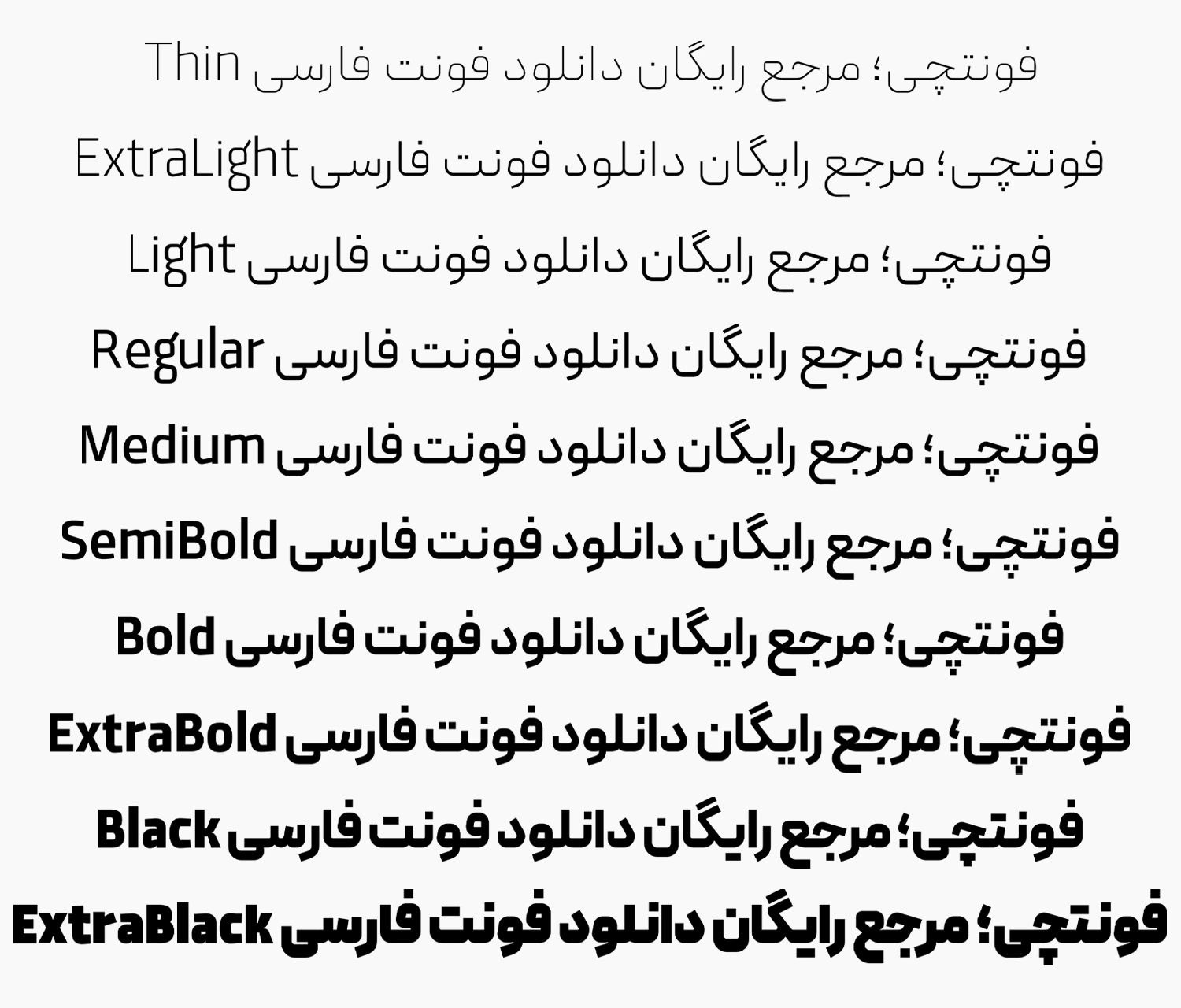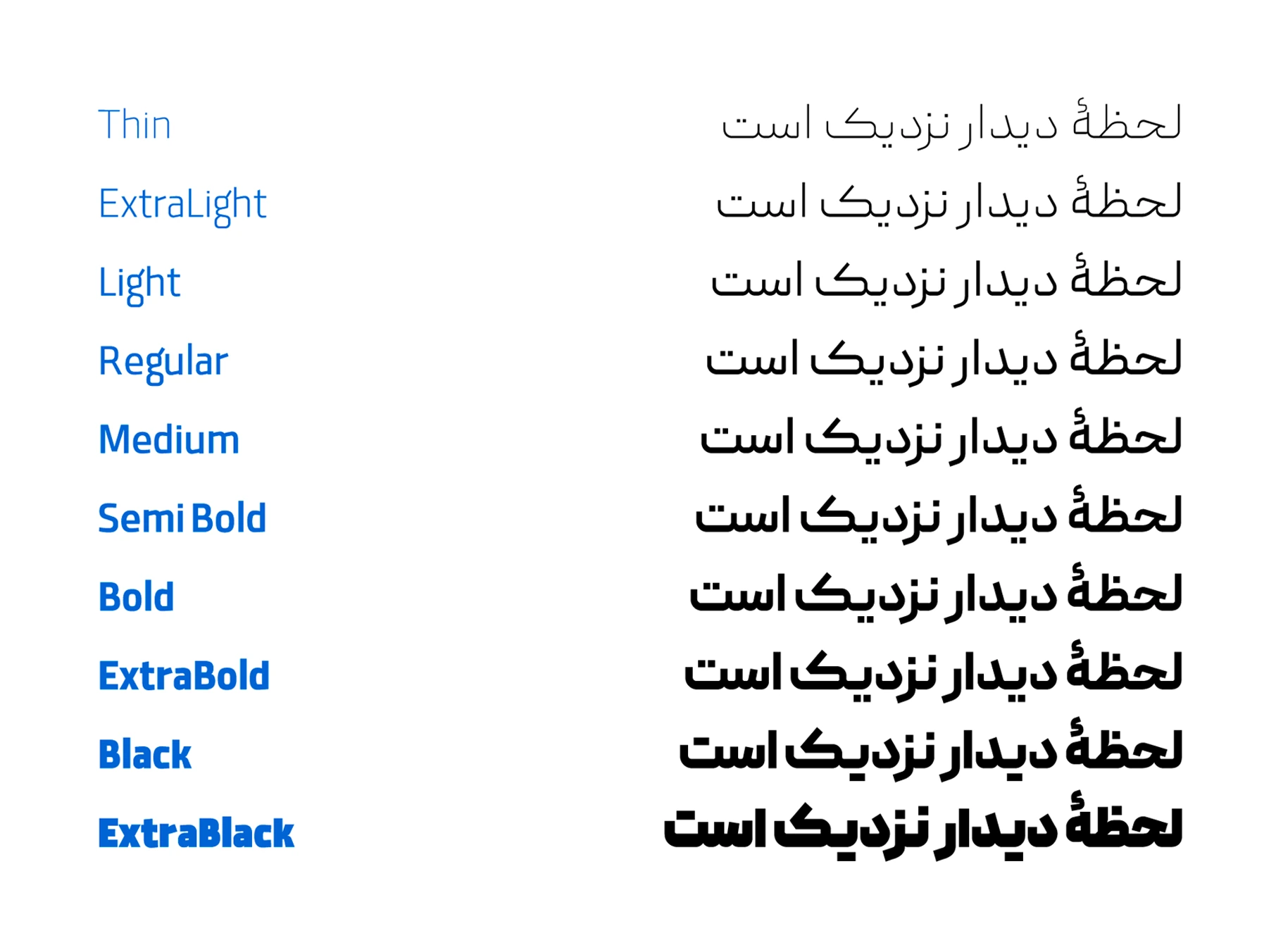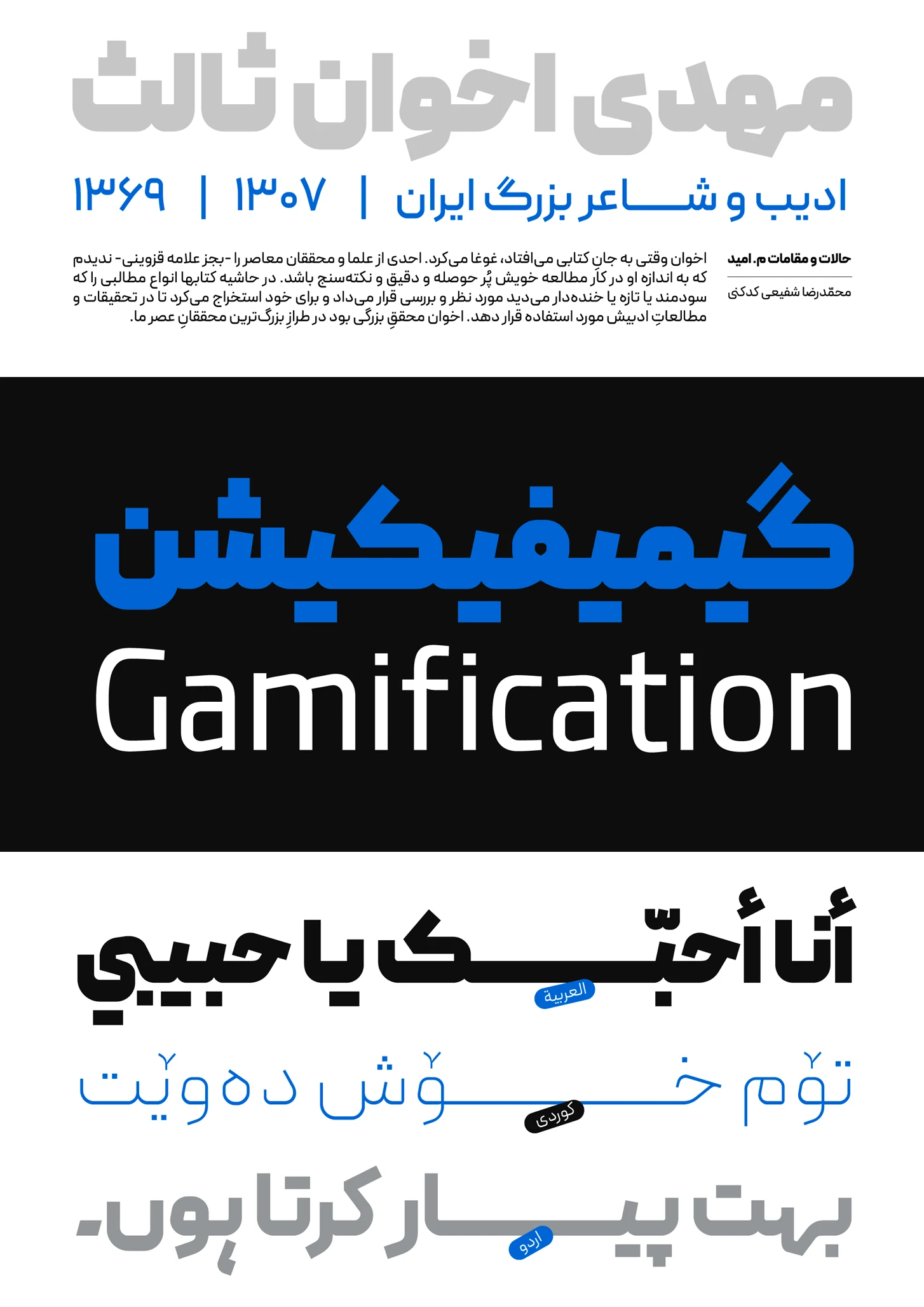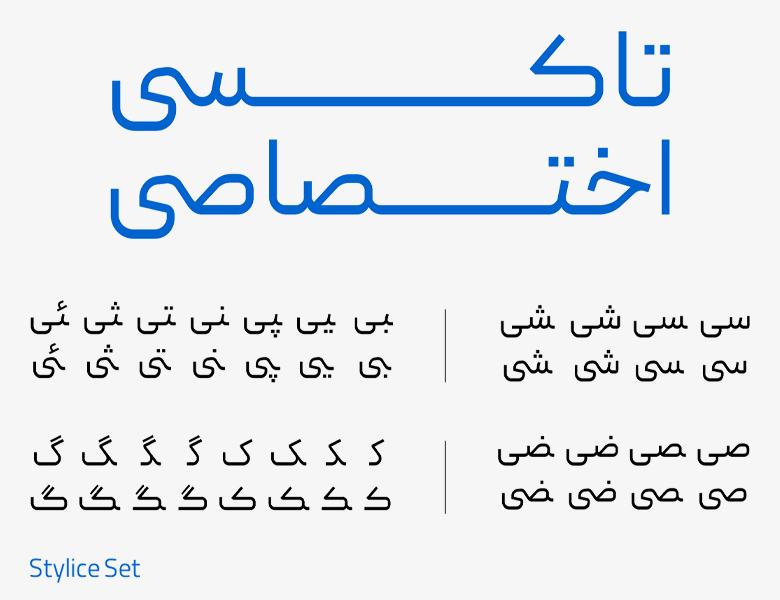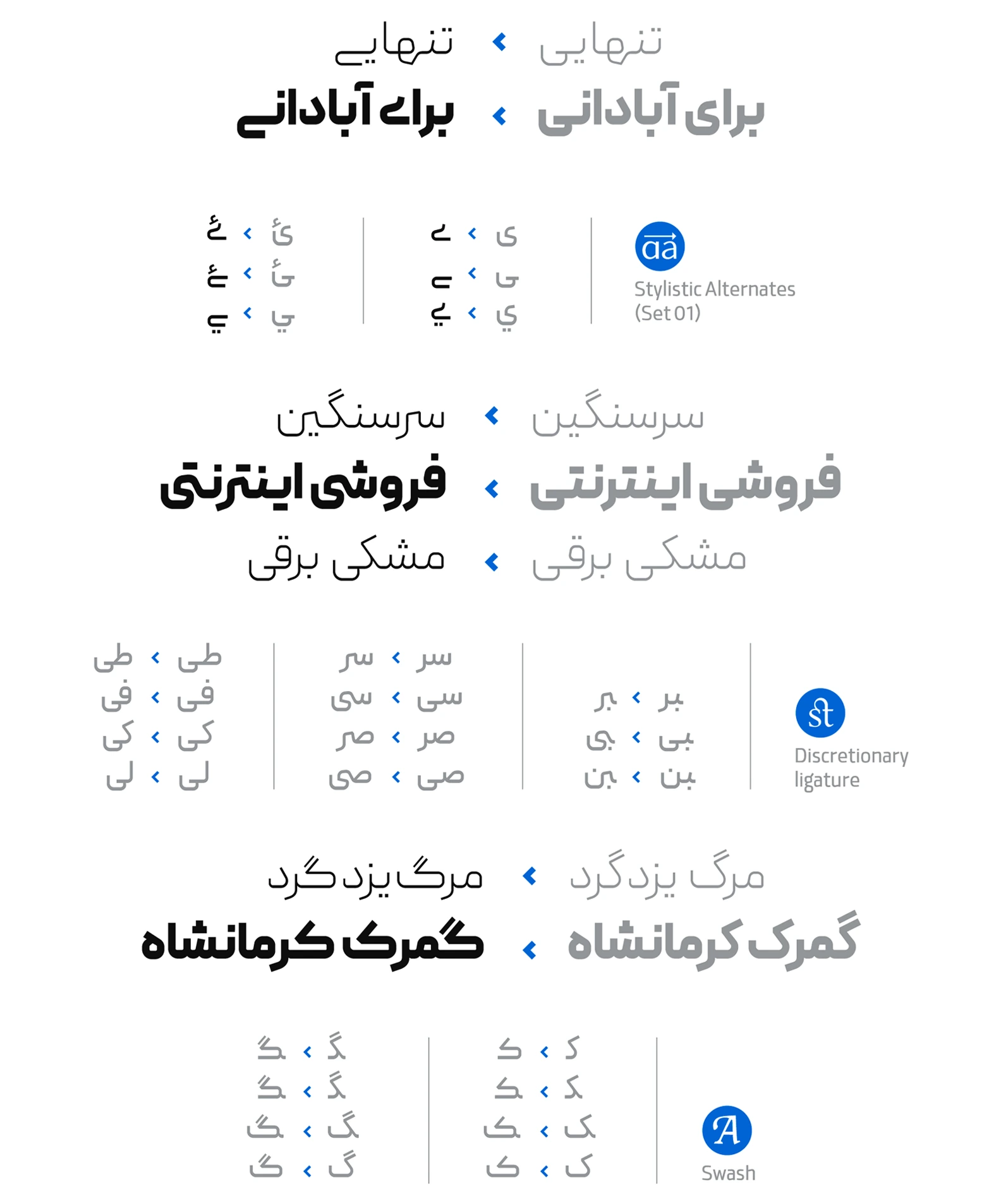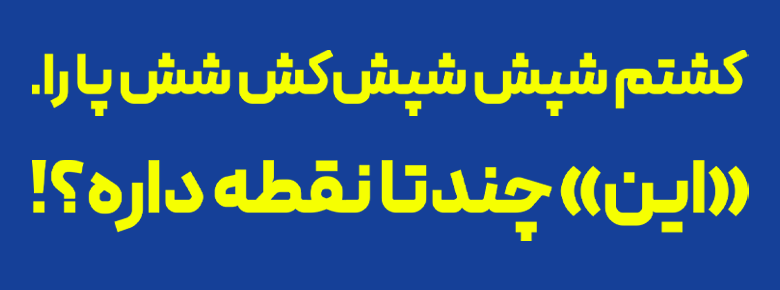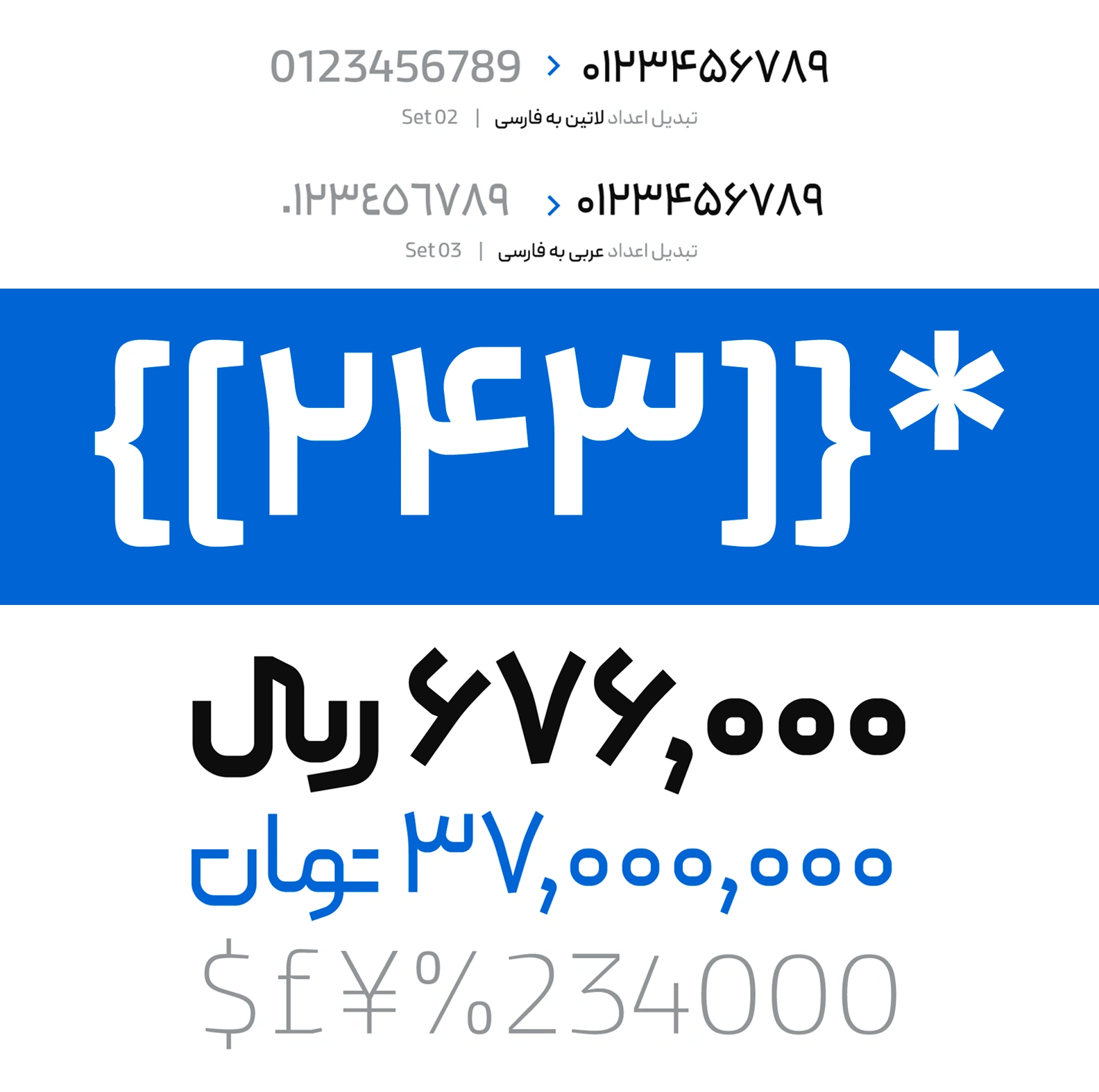
فونت پیدا (Peyda)
ایده طراحی و ساخت فونت پیدا (Peyda) در سال ۱۳۹۸ توسط سید ناصر خادم آغاز و در نهایت پس از یک سال تلاش شبانهروزی در سال ۱۳۹۹ منتشر شد. فونتی مناسب متن با طراحی سنس که دارای ضخامت و میزان پهنای ثابتی در تمامی بخشهای حروف، شکستگیها و منحنیها است. فونت پیدا رایگان نبوده و در ۳ بسته مختلف با وزنهای ۱۰ گانه منتشر شده است.
این فونت که ساختاری کاملا هندسی دارد، با کمی کنکاش در بطن آن میتوان آثاری را از خط نسخ مشاهده کرد که از آن الهام گرفته شده است. این فونت با اصالت دارای طراحی مدرن و هندسی است که مناسب تولید محتوا، کارهای تجاری و متنهای کوتاه و بلند است. از این فونت حتی میتوان به عنوان یک فونت عنوان استفاده کرد.
در ادامه این نوشته از وبسایت فونتچی به نقد و بررسی کامل فونت پیدا خواهیم پرداخت؛ فونتی که در تمامی وزنهای ۹ گانه خود، از ضخامت یکسانی در تمامی بخشهای حروف برخوردار است و با توجه به کنتراست بالایی که دارد، برای متنهای بلند و افزایش میزان خوانایی انتخابی بسیار عالی است.
معرفی و بررسی فونت پیدا (Peyda)
با توجه به نوع طراحی مدرنی که فونت پیدا دارد، انتخابی عالی برای استفاده در فضای وب و دیجیتال است. از این تایپ فیس پر انرژی میتوان در طراحی انواع بنر، تیترها و عناوین، تولید محتوا در شبکههای اجتماعی، ساخت اینفوگرافیکها و هر چیزی که فکرش را بکنید استفاده کرد.
یکی از چالشهای طراحیِ این تایپفیس اصرار بر وجود کاراکترهایی با فرمهای بهدور از پیچیدگی بود؛ از همینرو فضای چشم حروف دارای یک منطق مشخص است و به دلیل استخوانبندی مَفصلی و خطوط اصلی که عمودی و افقی هستند، کاراکترها فضاهای منفی منظمی دارند.
فونت پیدا دارای روحیهای مدرن است که به خوانایی آن سطح بالایی بخشیده است. همچنین برای متنهای کوتاه و نیمه بلند در حوزههای مختلف قابل استفاده است.
وزن و سبک فونت پیدا
فونت پیدا دارای پیشینه خانوادگی است؛ یعنی وزنهای مختلفی را از خیلی نازک تا سیاه شامل میشود که تمامی وزنها دارای پهنای ثابت و استانداردی در طراحی همه بخشهای حروف شامل چشمیها، منحنی، شکستگی و نقاط هستند که در مجموع یک خانواده ۱۰ وزنی را شامل میشود.
علاوه بر این تنوع وزنی، نسخه فونت پیدا وریبل تمامی وزنهای ۱۰ گانه را در خورد دارد که میتوانید با استفاده از دستورات Stylish در CSS یا نرم افزارهای گرافیکی مانند فتوشاپ از ترکیبات جایگزین و همه این وزنها در قالب یک فایل فونت تکی استفاده کنید.
تنوع بالای این فونت خانوادهدار که شامل ۱۰ وزن است، آن را برای استفاده در صنعت چاپ تا فضاهای مجازی به گزینهای که نمیتوان از آن چشمپوشی کرد تبدیل کرده است. خصوصا که برای استفاده از فونت پیدا در سایت نیز فرمتهای بهینه و کمحجم اراسه شده است.
پشتیبانی از زبانهای مختلف
فونت پیدا فارسی علاوه بر این زبان، از دو زبان عربی و انگلیسی نیز پشتیبانی میکند. بدون اینکه نیازی به استفاده از قلم دیگر داشته باشید، میتوانید به سادگی زبانهای مختلف سهگانه را در متون خود استفاده کرده و از یک قلم یکپارچه برای متن خود بهرهمند شوید.
در فونت عربی امکان استفاده از تمامی اعراب فراهم شده و همچنین اعداد «۴، ۵ و ۶» که ساختاری متفاوتتر از اعداد در زبان فارسی دارند قابل استفاده است.
در نسخه ۴.۰ فونت پیدا که در مرداد ۱۴۰۴ منتشر شد، پشتیبانی از زبانهای اردو و کوردی نیز به این فونت افزوده شده است که تنوع استفاده از گلیفها را در این فونت بیشتر کرده است.
گلیفهای فونت پیدا فارسی برای زبان عربی بهصورت مشترک طراحی شده است. اما حروف مانند «ک، ی، و، ه» عربی که دارای ظاهر متفاوت از نظر همزه یا نقطهگذاری هستند، گلیف خاص خود را دارند که در صورت انتخاب صفحه کلید عربی با گلیف خاص خود تایپ خواهد شد. در اعداد نیز به همین شیوه عمل شده است.
امکان استفاده از حروف جایگزین
قابلیت دیگر فونت رایگان پیدا امکان استفاده از حروف جایگزین یا همان Stylice Set است تا امکان زیبا سازی و تایپ برخی کلمات را به شکلهای دیگر فراهم کند. در حال حاضر حروفی همچون «کـ»، «گـ» و «ـی» دارای ساختار جایگزین هستند که با استفاده از راهنمای موجود در بسته دانلود فونت پیدا میتوانید این حروف را با شکل متفاوتتری تایپ کنید.
علاوه بر حروف بالا، یک سری ترکیبات مشخص دوتایی مثل «سی، شی، صی، ضی، بی، پی، نی، تی، ثی، ئی» دارای ساختار جایگزین در چند سبک مختلف هستند که با توجه به چسبندگی به حروف دیگر یا جدا بودن، میتوان آنها را با ظاهر متفاوت نیز تایپ کرد که در تصویر بالا ترکیبی از هر دو ساختار ترکیبی این فونت را مشاهده میکنید.
ترکیبات دیگری نیز مطابق تصویر بالا به نسخه ۴ فونت پیدا افزوده شده است. با استفاده از این ترکیبات متنوع امکان نمایشیتر کردن فونت برای کارهای تبلیغاتی و گرافیکی فراهم میشود که به دیده شدن محتوای شما کمک بیشتری میکند.
پشتیبانی از نقطه گذاری چسبان و جدا
در فونت پیدا میتوانید نقاط را در زبانهای فارسی و عربی به صورت جداگانه یا چسبان به هم استفاده کنید. در حال حاضر نقاط استفاده شده در این فونت همگی به شکل مربعی هستند و خبری از نقطهگذاری گرد در آن وجود ندارد.
- اصلاح فرم بعضی از حروف و تنظیم فاصلهی حروف در زبان لاتین
- تغییر دستهبندی کاف و گاف کشیده از Stylistic Set به Swash